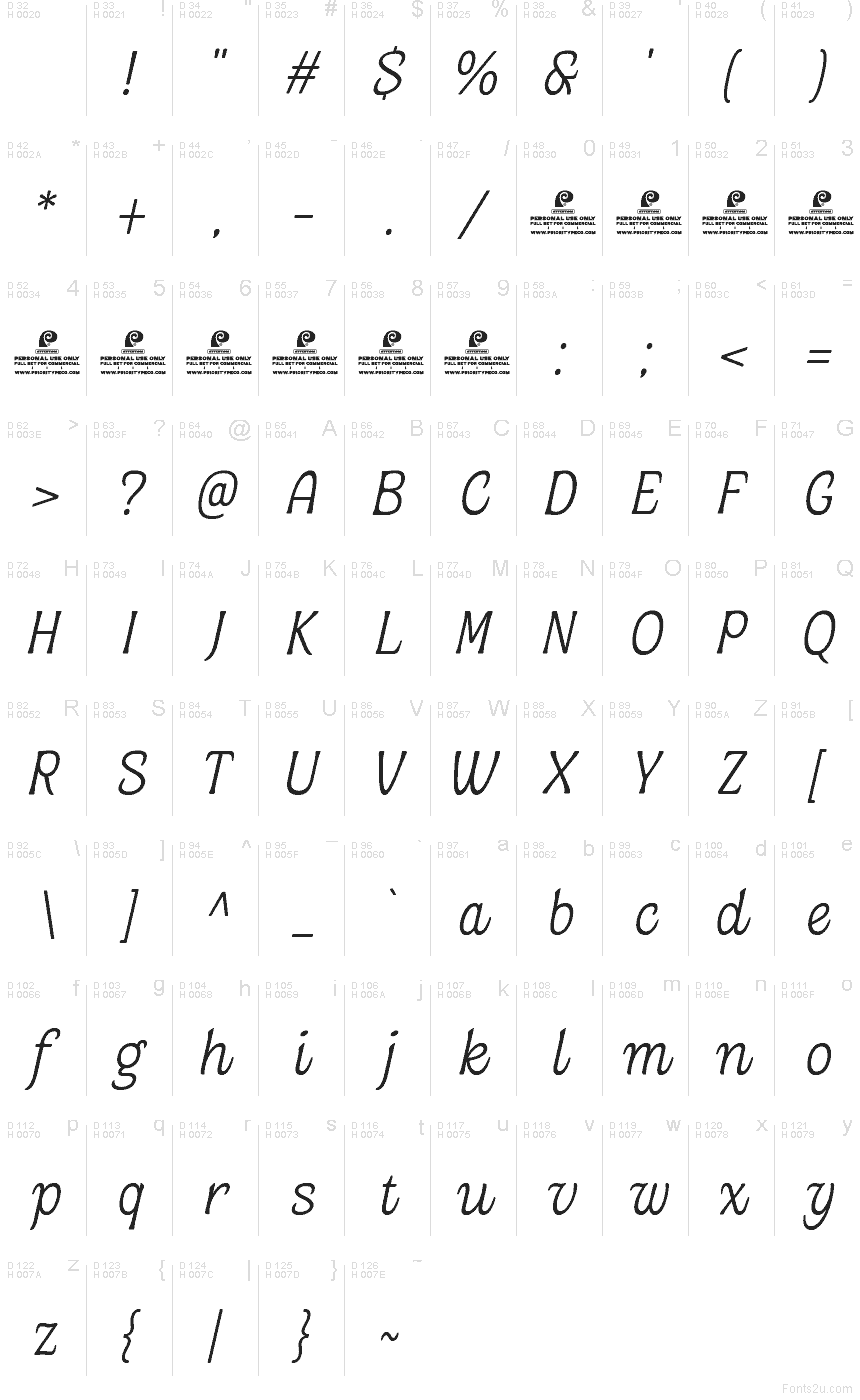
Ombre Nouveau, da Prioritype Co., é uma fonte display gratuita em itálico com influências do Art Nouveau, marcada por curvas longas e fluidas e um ritmo leve e arejado. As letras inclinam-se suavemente para a frente com um toque caligráfico, enquanto as aberturas altas e as formas delicadamente alongadas mantêm a fonte equilibrada, sem excessos.
É excelente para branding de boutiques, embalagens de perfumes ou joias, menus de cafés, capas de livros e cartões de títulos de filmes onde um pouco de glamour clássico ajuda a compor a cena. Como fonte gratuita, também é perfeita para títulos curtos, iniciais e logotipos tipo monograma, pois essas curvas elegantes e traços alongados conferem uma presença decorativa distinta, mesmo em poucas letras.